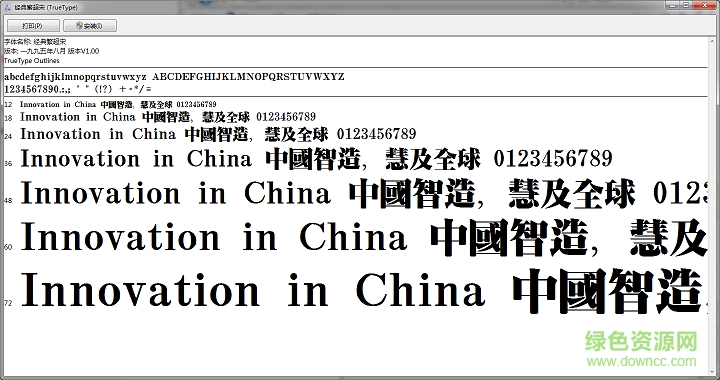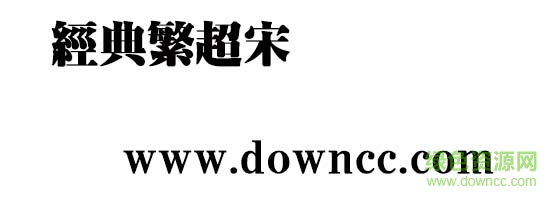
經(jīng)典繁超宋字體是一款中文繁體字體。該字體結(jié)合了宋體的特色,筆畫粗細(xì)地方都很清晰,結(jié)構(gòu)明了,需要的朋友,趕快來綠色資源網(wǎng)下載體驗(yàn)吧!
1.中國的字體設(shè)計(jì)是在印刷術(shù)的產(chǎn)生和發(fā)展中應(yīng)運(yùn)而生的。在古代,中國的字體設(shè)計(jì)曾有過輝煌的歷史時期,在宋朝時進(jìn)入黃金時代。
2.清朝末年,鉛字排版印刷術(shù)傳入中國,字體設(shè)計(jì)進(jìn)入鉛字時代。這個時期的字體設(shè)計(jì)既要帶有傳統(tǒng)文化的審美慣性,又要符合鉛字印刷的工藝要求,字體設(shè)計(jì)走到了轉(zhuǎn)折的關(guān)口。
3.鉛字印刷是印刷走入機(jī)械化、工業(yè)化時代的標(biāo)志,但在這一時代里,印刷字體設(shè)計(jì)卻始終無法超越手工勞動的制約,無法擺脫刻模、鑄字、撿字、排版等一系列印前繁雜工藝的束縛